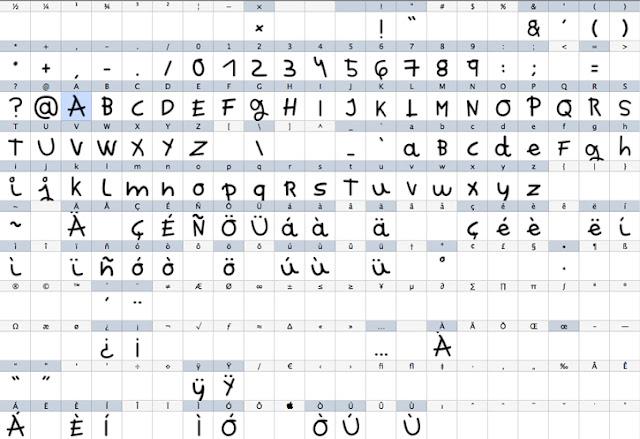
La Tipografía Anna por la igualdad social
Os presentamos la tipografía Anna creada por Anna Vives, una chica de 27 años con sindrome de Down, apasionada del diseño y el dibujo. La tipografía a sido creada dentro del proyecto "sumant capacitats" (sumando capacidades) que tiene como objetivo representar a todo el colectivo de personas discapacitadas, conseguir difundirla y potenciar los valores asociados a la letra: la igualdad social y la importancia del trabajo en equipo sumando capacidades.
Y la cosa no se queda hay, uno de los sueños de Anna era que la tipografía llegara a su equipo favorito, el Fc Barcelona. Pues bien el club se a hecho eco de este deseo y estudia como incorporar la tipografía Anna en las diferentes comunicaciones y acciones del club, incluso, según el periódico deportivo Sport, se baraja la posibilidad de incluirla en los dorsales de las camisetas, desbancando a la que comentemos hace un tiempo en este mismo blog, aunque esta decisión no corresponde tanto al club sino al patrocinador deportivo, en este caso Nike. ¿ que opináis llegaremos a ver esto?